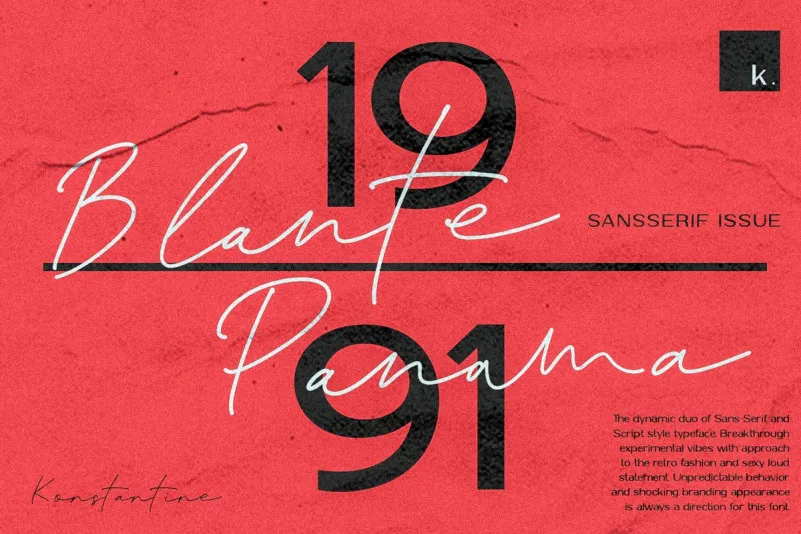
A Blante Panama Font Dou é uma fonte que combina duas categorias inusitadas em um design único. Ela apresenta um par de tipo serifless grosso e fino, combinado com linhas à mão livre que imitam o estilo da canetinha. Inspirada no retorno ao vintage e na estética provocativa, ela oferece uma aparência surpreendente e uma personalidade única. Esta fonte é perfeita para quem busca um toque de modernidade em seus designs enquanto mantém uma conexão com os anos 80 ou 90. Seja você um designer gráfico, um criador de conteúdo digital ou simplesmente alguém que adora experimentar novas formas de expressão visual, Blante Panama Font Dou pode ser a escolha perfeita para seu projeto. Com sua personalidade inovadora e aparência chocante, ela vai transformar qualquer design em algo singular e irresistível.